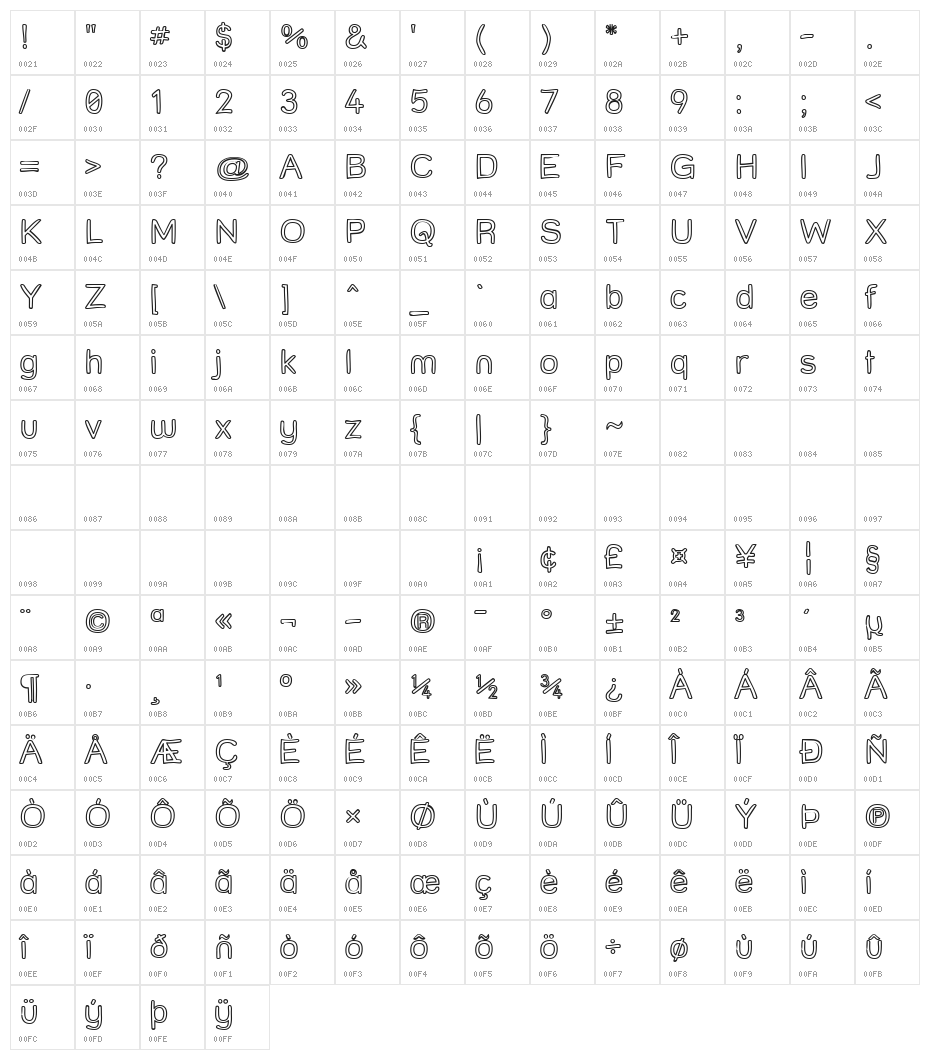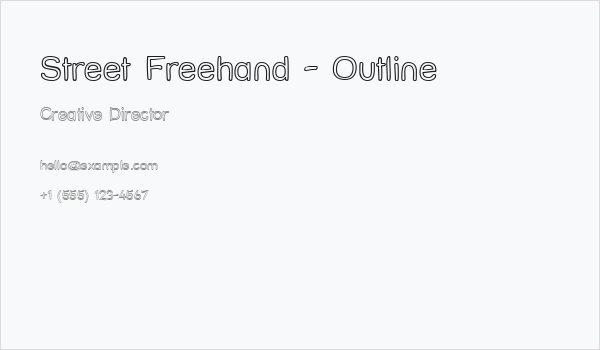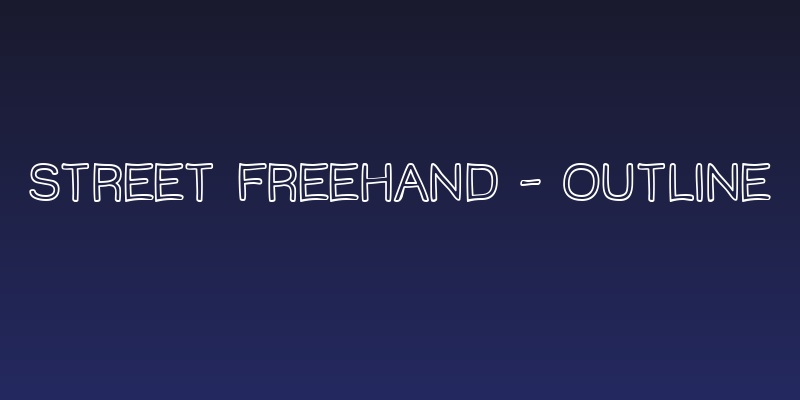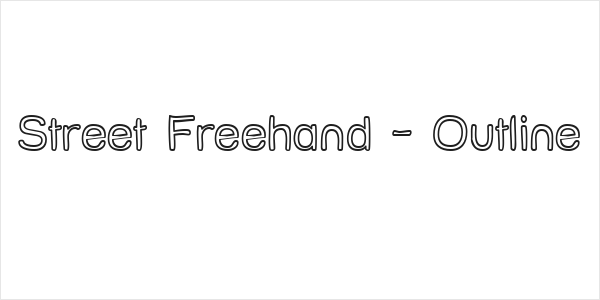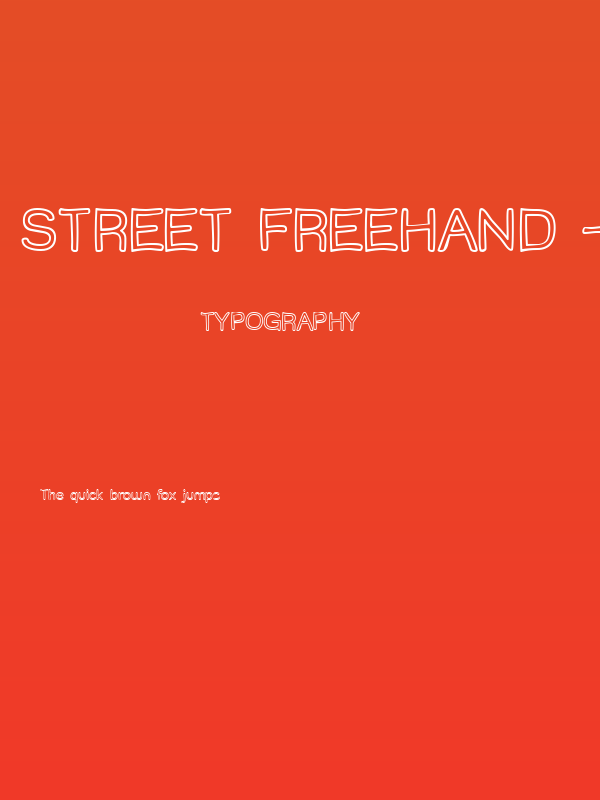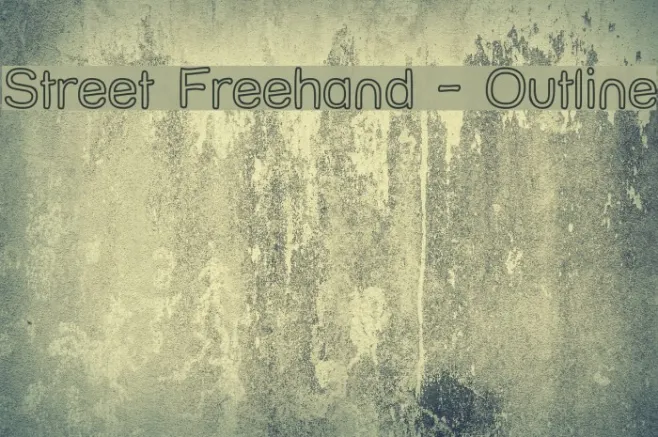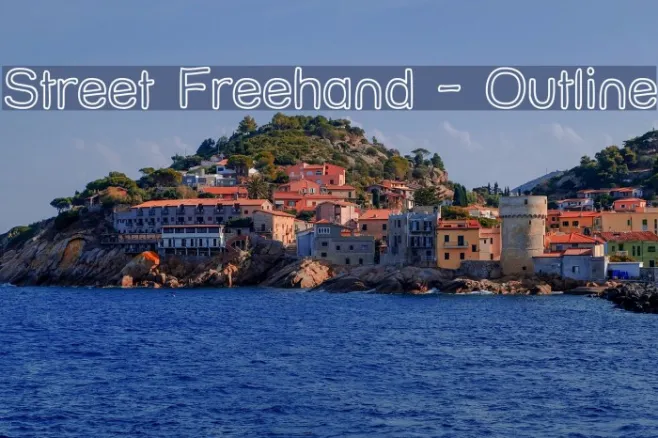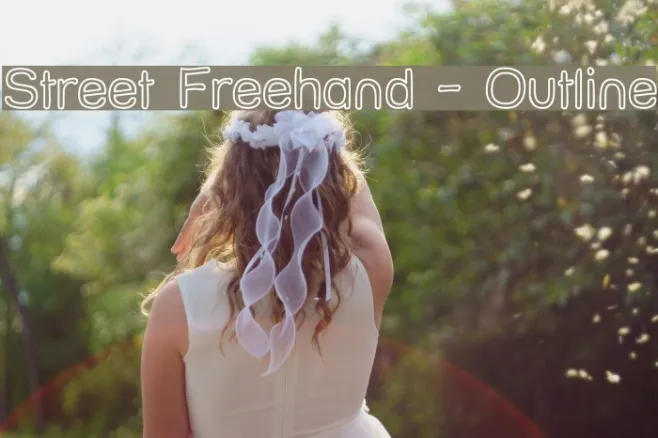
Street Freehand - Outline Font
| Style général | Casual, Playful |
| Cas d'utilisation | Headlines, Posters, Branding |
| Projets proposés | Ideal for creative projects such as posters, invitations, children's books, and branding that requires a fun and approachable aesthetic. |